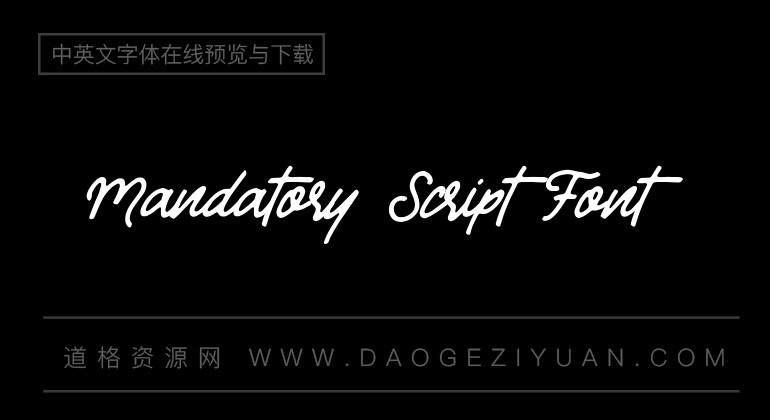
Mandatory Script Font
Mandatory Script是一种手写风格的字体,其特点在于其轻盈、流畅的笔画和自然的手写风格。这种字体非常适合用于设计书籍封面、标题、海报或其他需要突出文本的设计项目。 Mandatory Script字体的字母形状是流畅的连笔字母,其笔画有时会倾斜或重叠,以此来强调字母之间的连续和流畅性。该字体的笔画也变化丰富,有些笔画会延伸或卷曲,以此来增强字体的表现力。 总之,Mandatory Script是一种非常优美和具有表现力的字体,可以帮助设计师在设计项目中突出文本,并为项目增添一份流畅的美感。
Mandatory Script Font是一款非常不错的手写艺术字体,具有很好的视觉感,适合于文化类的宣传设计、商业类品牌的广告和产品包装设计以及个性化文字排版等较多场景。